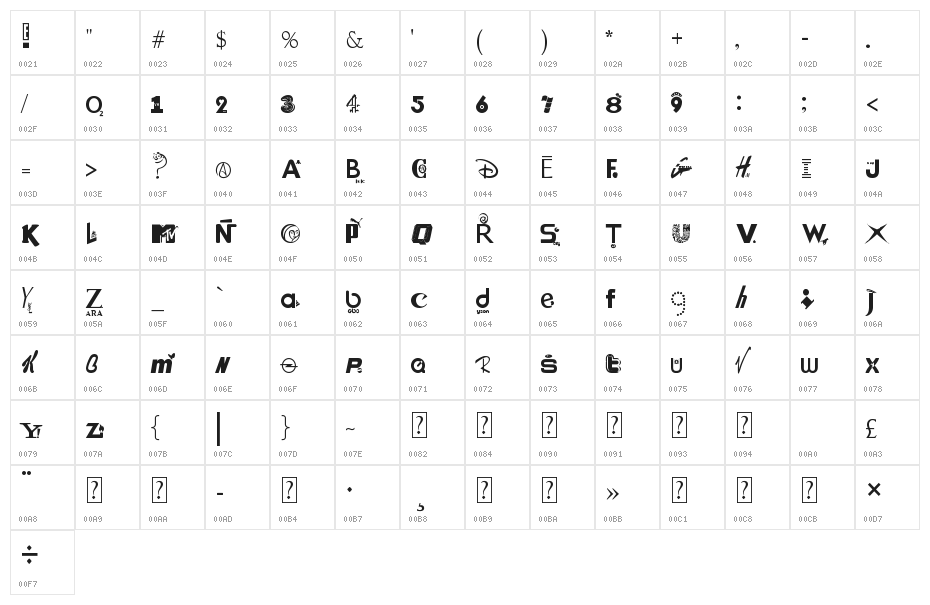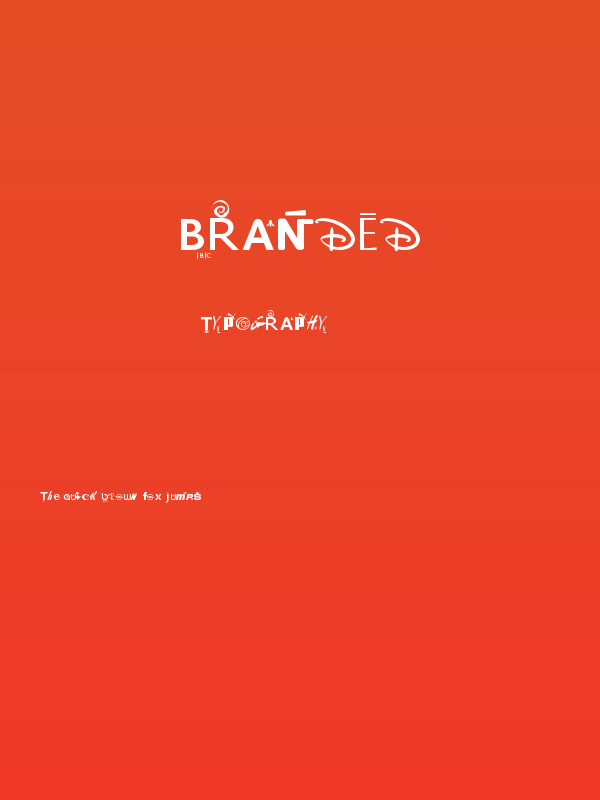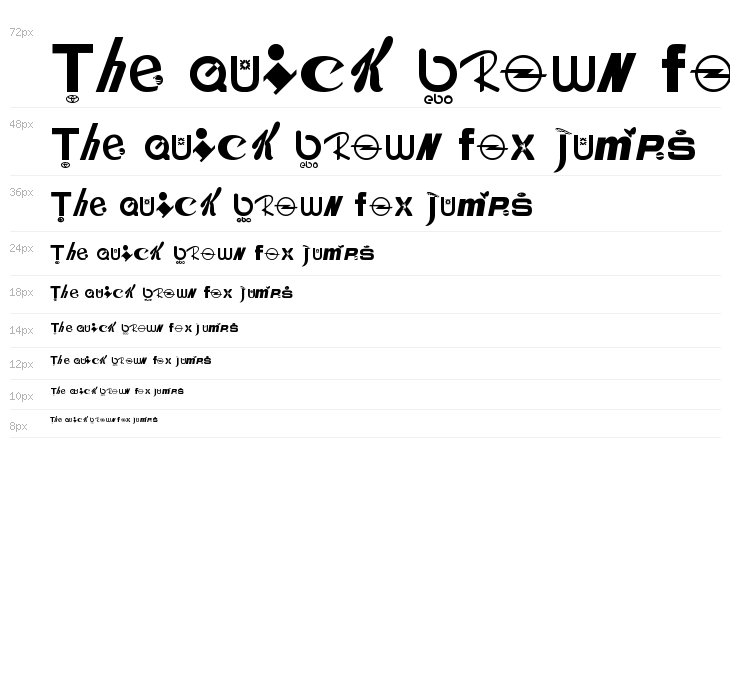
BRANDED Font
| Caso d'uso | Logos, Artistic displays, Themed designs |
| Progetti proposti | Ideal for creative projects, themed designs, or artistic displays where brand recognition and playful aesthetics are desired. |